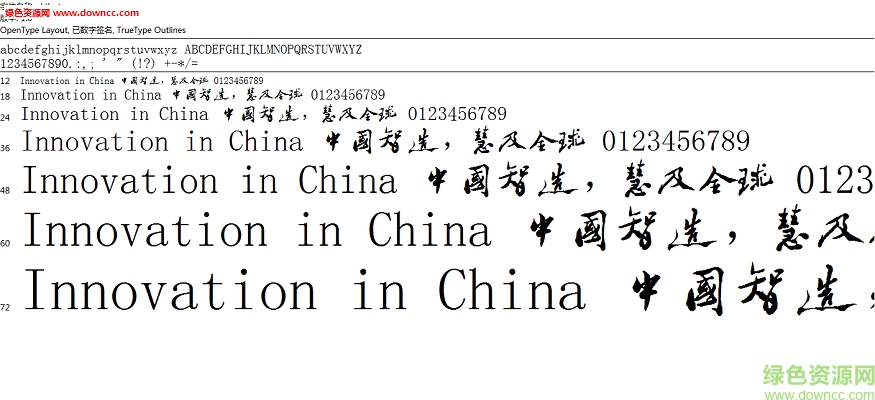
字酷堂鄭板橋行書體高度還原了鄭板橋的行書字體,字體極具藝術(shù)風(fēng)格,每筆每畫都給人一種飄逸灑脫的感覺,而在飄逸之余不失大氣,更顯難得,感興趣的朋友們快來下載吧!
字酷堂鄭板橋行書體是一種應(yīng)用于設(shè)計(jì)方面的中文簡體字體,該字體非常藝術(shù),字形飄逸大方,整體效果非常出色,可應(yīng)用于文學(xué)設(shè)計(jì)、藝術(shù)創(chuàng)作、雜志報(bào)刊、印刷包裝等領(lǐng)域
字酷堂字體制作的底稿多是采用掃描近代書法家的字帖和字跡制作而成,故書法味道挺濃(也正因?yàn)榇耍阅壳白挚崽米煮w多為繁體字庫,簡入繁出(輸入簡體字直接顯示為繁體))適合用于海報(bào)設(shè)計(jì)、banner設(shè)計(jì)、包裝設(shè)計(jì)、古籍排版、網(wǎng)頁設(shè)計(jì)等方面。